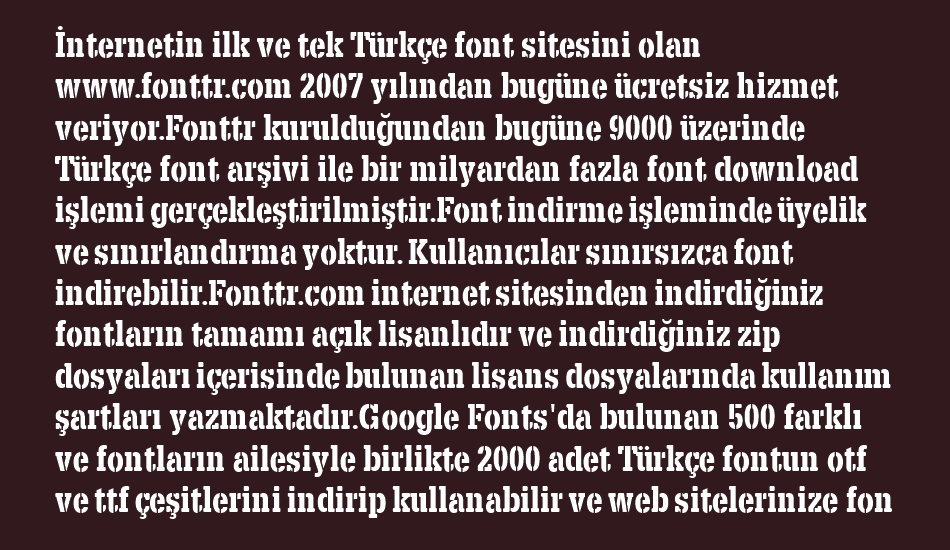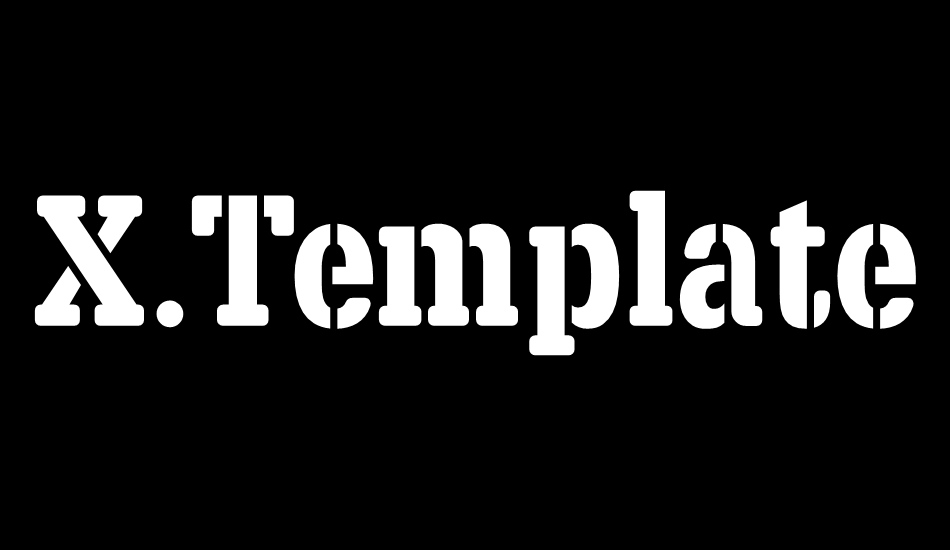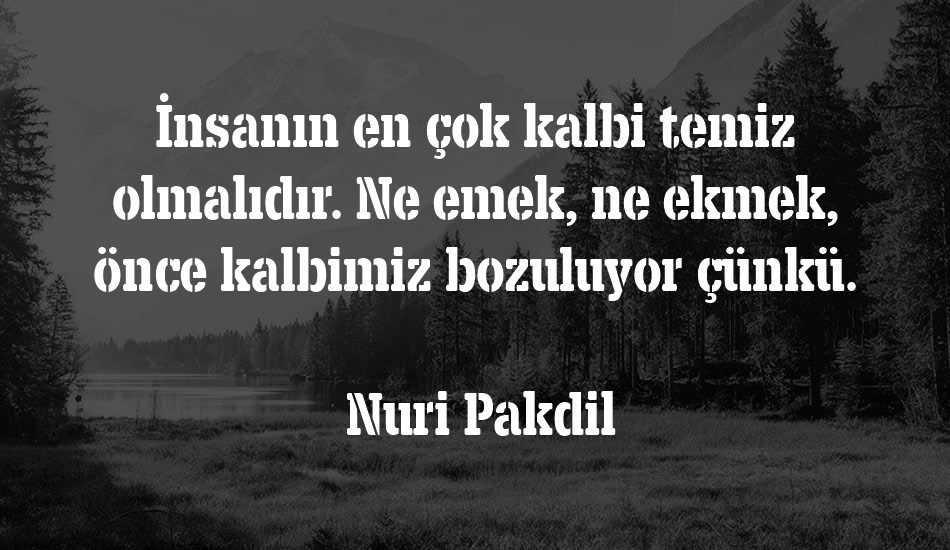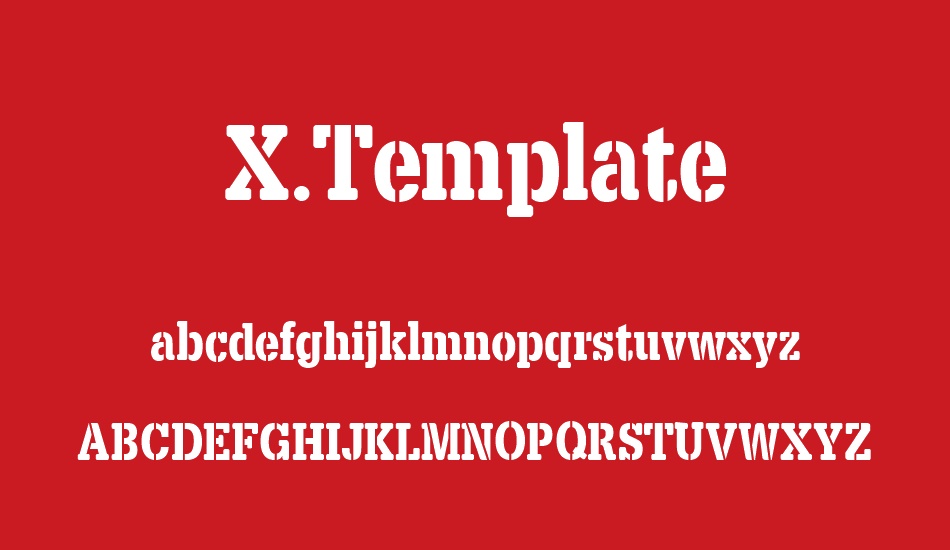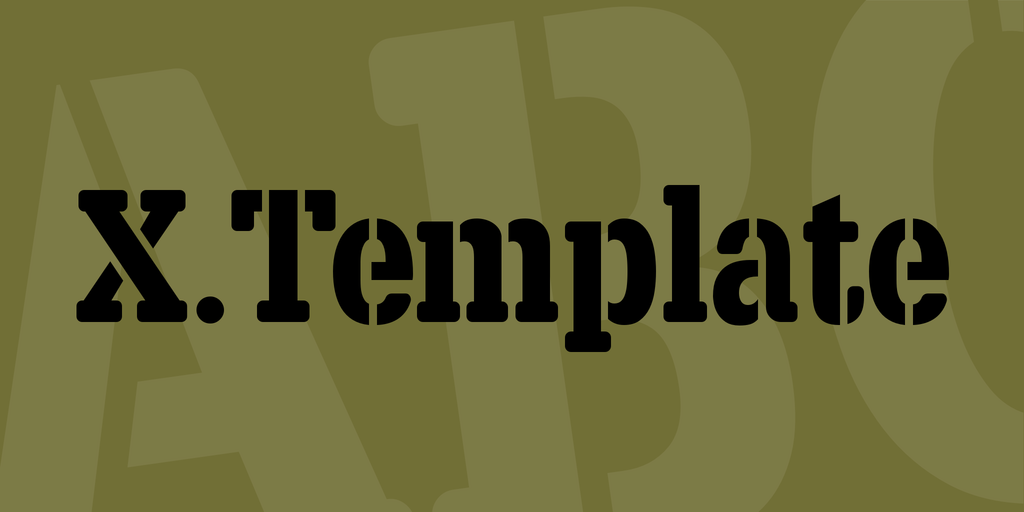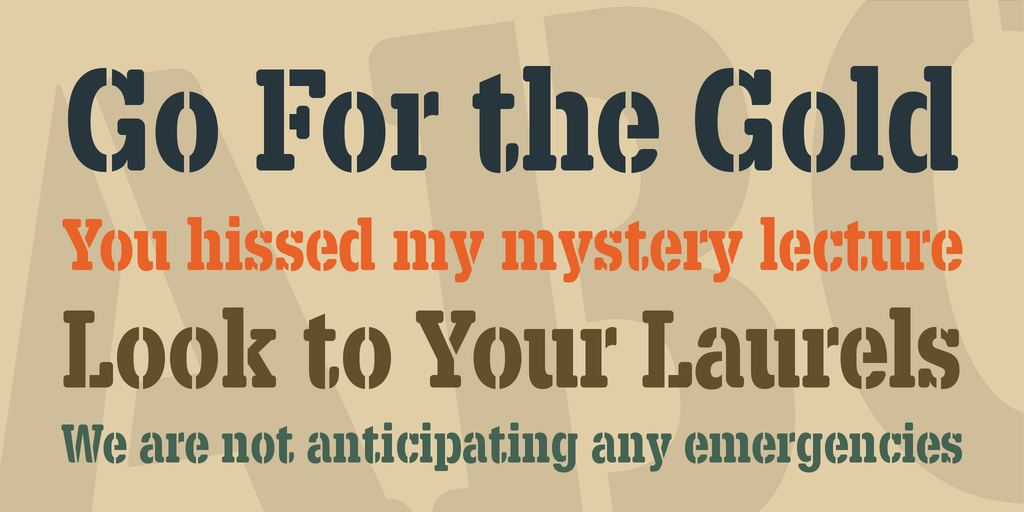
X.Template Font font
X.Template font
X.Template Font font
X.Template es una tipografía Stencil, negra y condensada, con serifas cuadradas de acabado redondeado. Una virguería para diseño de carteles y posters.